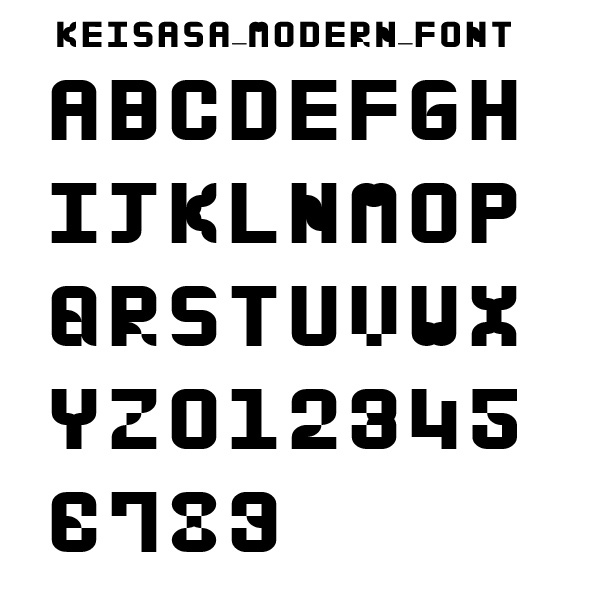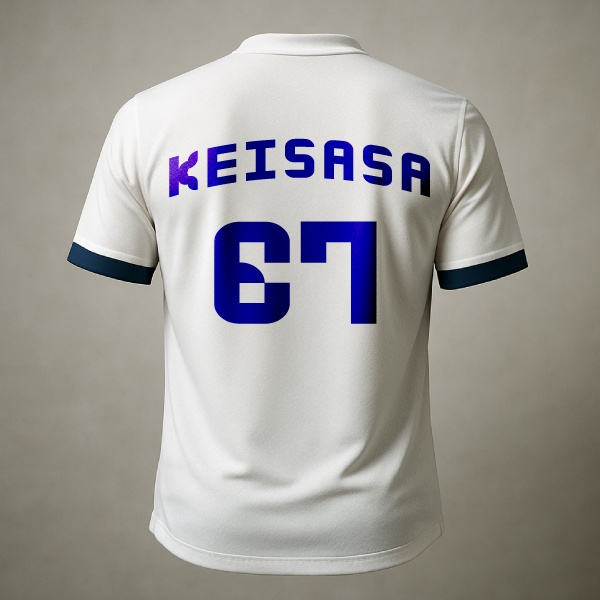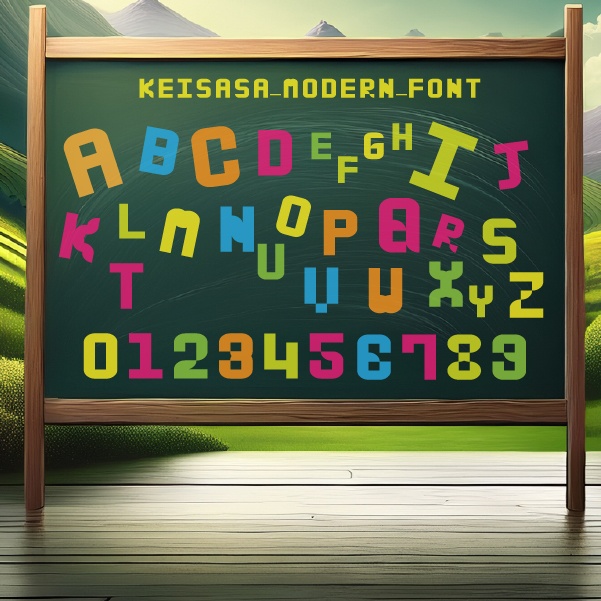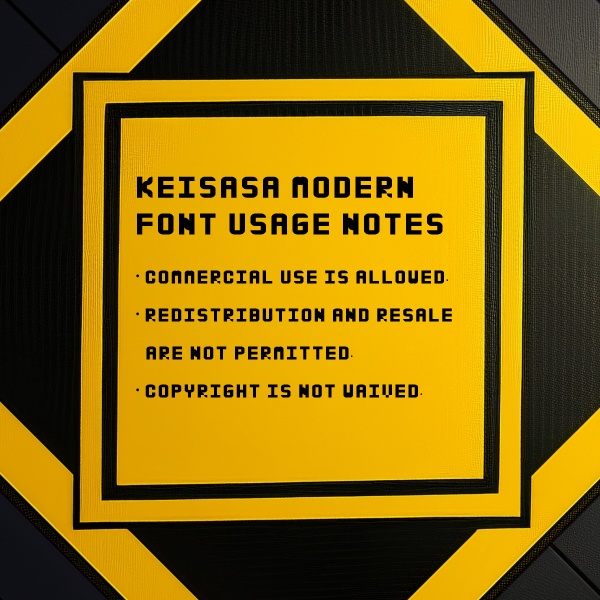
【商用可】 Keisasa_Modern_font.ttf|デジタル風ディスプレイフォント
Keisasa Modern Font Keisasa Modern Fontは、グリットに当てはめて作成し、デジタル系に合うように作成致しました。 モダンで洗練されたデザインを特徴としたフォントで、見出しやロゴ作成に最適です。シンプルでありながらも強い印象を与え、どんなプロジェクトにもピッタリ合うスタイルです。四角と丸のバランスが絶妙で、視覚的に心地よいデザインを実現します。大文字と数字のみです。 スペック フォント形式:TrueTypeフォント(.ttf) スタイル:モダン、シンプル、クリーン 対応言語:日本語および英語(アルファベット) 使用可能なソフトウェア:Adobe Illustrator、Photoshop、InDesign、Microsoft Word、Google Docs など ライセンス:商用利用可能(個人・商業利用ともにOK) 特徴とこだわり Keisasa Modern Fontは、見出しやロゴデザインに最適なフォントです。シンプルなラインと丸みを帯びた形がバランスよく組み合わさっており、どんなデザインにも自然に馴染みます。モダンな印象を与えるこのフォントは、ウェブデザインや広告、ポスター、名刺など、視覚的に印象を与えたい場面で活躍します。 デザインにおけるミニマリズムを重視しており、細部にわたる精密な作り込みが施されています。ロゴ作成にも非常に向いており、簡潔でありながらも特徴的なデザインを引き立てます。 制作の道のり このフォントは、シンプルさと実用性を兼ね備えたフォントを作りたいという思いから生まれました。直線と曲線の美しい調和を追求し、どんな用途でも使いやすいフォントデザインを実現しています。制作の過程では、視認性と美しさの両立を目指しました。 ライセンスについて このフォントは商業利用を含む幅広い用途にご使用いただけますが、再配布は認めておりません。著作権は放棄していませんので、著作権を尊重した上でご利用ください。 Keisasa Modern Fontは、シンプルさと美しさを兼ね備えたフォントで、見出しやロゴデザインを一層引き立てます。ぜひ、あなたの次のデザインプロジェクトにお役立てください。 収録文字 A〜Z 0〜9 Keisasa Modern Font is a modern, sleek typeface designed with balance and elegance. Perfect for headlines, logo creation, and various design projects, this font combines sharp lines with subtle curves, making it versatile and visually appealing for a wide range of uses.Only uppercase letters and numbers. Specs Font Format: TrueType Font (.ttf) Style: Modern, Simple, Clean Supported Languages: Japanese and English (Alphabet) Compatible Software: Adobe Illustrator, Photoshop, InDesign, Microsoft Word, Google Docs, etc. License: Commercial use allowed (both personal and commercial use) Features & Design Keisasa Modern Font is ideal for creating headlines and logos. The harmonious balance of sharp lines and soft curves blends seamlessly into any design, providing a clean yet bold look. This modern font is perfect for use in web design, advertising, posters, business cards, and other projects that demand visual impact. The design emphasizes minimalism while ensuring high legibility. It's not only aesthetically pleasing but also functional, making it a great choice for creating unique logos and impactful visuals. The Creative Process This font was created with the goal of achieving simplicity and usability. Careful attention was paid to the balance between straight lines and rounded forms to create a versatile and beautiful font that suits a variety of applications. The font's clean and modern aesthetic is the result of meticulous craftsmanship. License Terms This font can be used for commercial purposes, but redistribution is not allowed. Copyrights are not waived, so please respect the intellectual property rights when using the font. Keisasa Modern Font is the ideal choice for those looking for a sleek, modern typeface that works perfectly for headlines, logos, and more. Try it in your next creative project and see how it elevates your designs! This is an original TTF font designed by Japanese artist Keisasa. Available for commercial use. Ideal for creative design, games, and more.